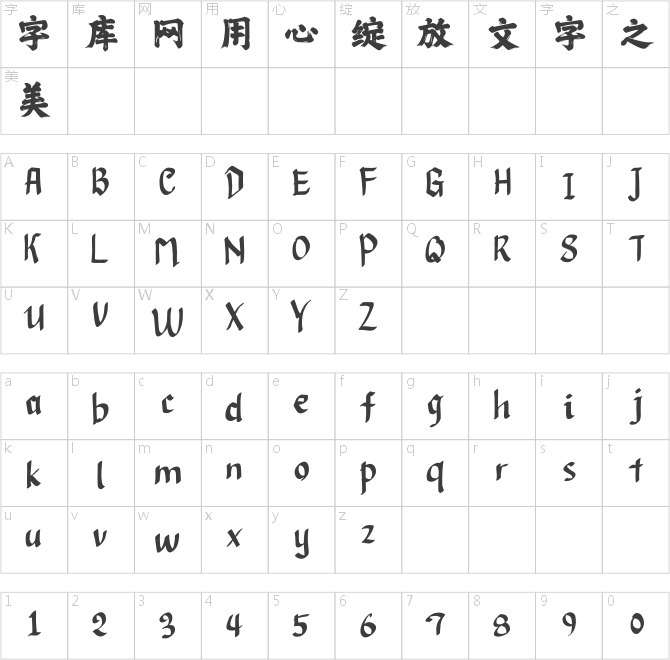
字体名称: 汉仪新蒂佛塔书
汉仪新蒂佛塔书
汉仪新蒂佛塔书字体下载HanyiSentyPagoda
汉仪新蒂佛塔书是一款综合了历代匾额,特别是佛教古塔古迹书法特征的一款字体。设计师通过严谨的分析及再创作,再现了大楷墨迹书写的苍劲气势、以及庄严雄壮的佛教古迹书写风格。该字体适用于国风文化类的设计环境。